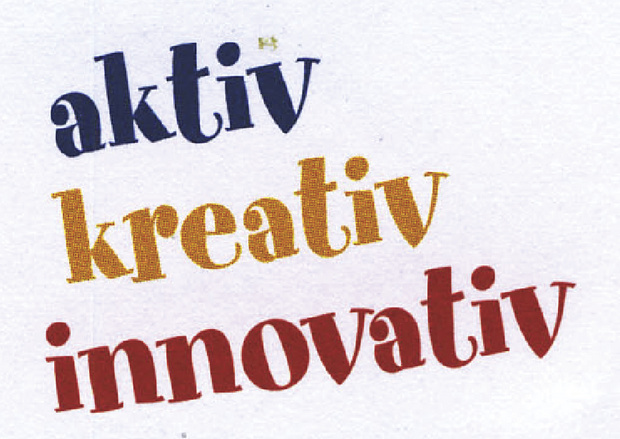
Schrift ähnlich Ravie
Gerne. Die Schrift hat nun mal überhaupt nichts mit innovativ oder kreativ zu tun. Das sollte dir der Spaß sagen.
Ja, gestern durch Zufall bei meiner LAG (Lebensabschnittsgefahr) von einer Karnevalsübertragung im TV belästigt worden, ganz fett im Hintergrund die Spumoni als Leuchtschrift. *SCHRECK* Richtig neonbunt und in Vollfarbe. *GRUSEL*